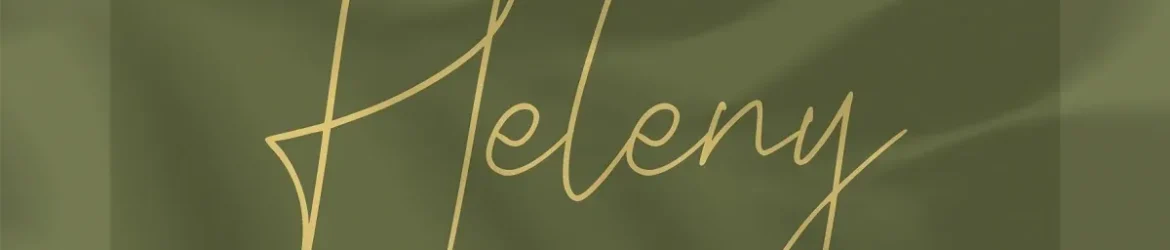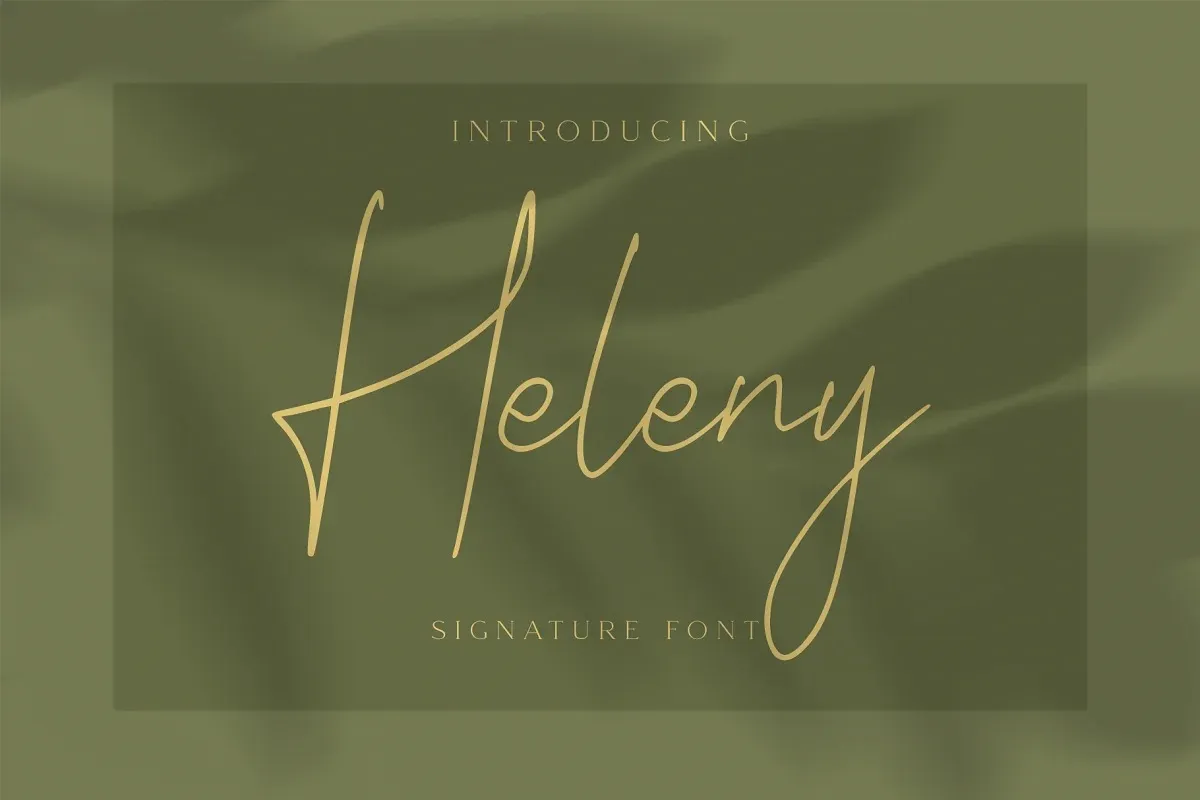
Heleny Font – Fonte Grátis
Heleny Font
A Heleny Font é uma elegante tipografia script monoline criada pela Craft Supply Co, ideal para aqueles que desejam dar vida aos seus projetos digitais com um estilo sofisticado e único. Esse tipo de letra perfeito para marcas de moda, lojas virtuais, blogs de tendências ou boutique de casamentos, proporcionando uma aparência elegante e chic sem precisar recorrer a estilos mais complexos. Seja você designer, digital artista ou apenas alguém interessado em adicionar um toque especial aos seus projetos digitais, Heleny é certamente o tipo de fonte que vai revolucionar como você cria texto. Em seu catálogo de fontes script disponíveis gratuitamente e por pagamento, a Heleny oferece uma opção versátil para designers criarem projetos que exibem sofisticação e originalidade.